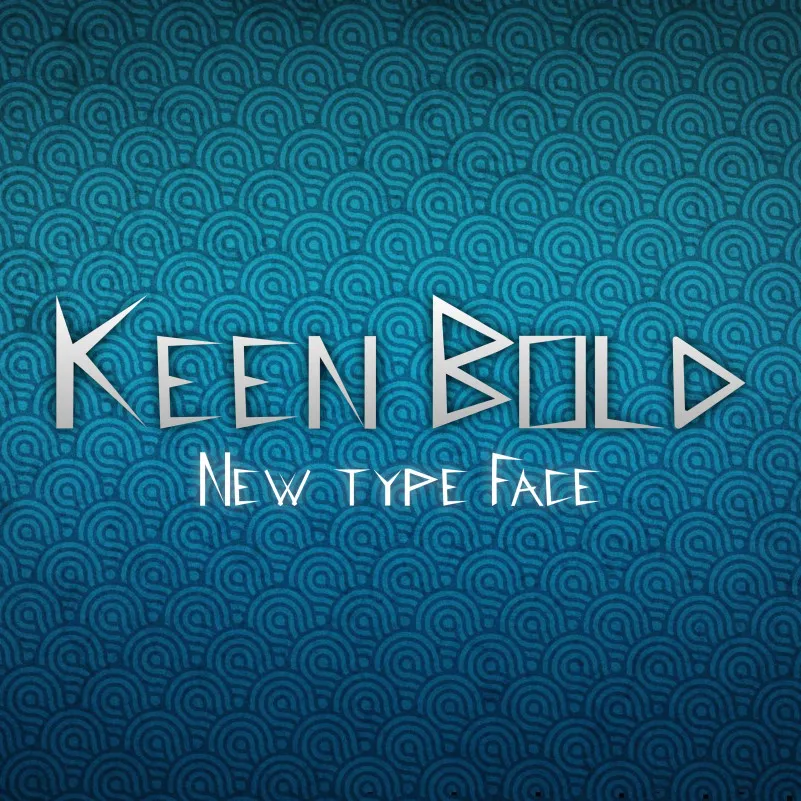
Keen Bold Display Font – Download Grátis
Descubra a elegância dos tempos modernos com a ‘Keen Bold Display Font’, uma serif font exclusiva criada pelo designer chasim. Esta escolha é perfeita para quem busca um estilo sofisticado e duradouro em seus projetos digitais. Com linhas arredondadas e detalhes bem definidos, esta fonte combina elegância clássica com uma personalidade moderna que vai acentuar qualquer texto. Perfeito para aplicativos de design gráfico, sites corporativos ou até mesmo materiais publicitários, a ‘Keen Bold Display Font’ é o toque final que seu projeto precisa. Se você está procurando por uma fonte que combine elegância e força, este é o ponto de partida perfeito. A ‘Keen Bold Display Font’ não apenas adiciona um brilho à sua identidade visual, mas também oferece a conveniência de ser fácil de usar em diferentes tamanhos e formatos. Que tal adicionar ao seu portfólio esta versão robusta da serif font?
Designer: chasim